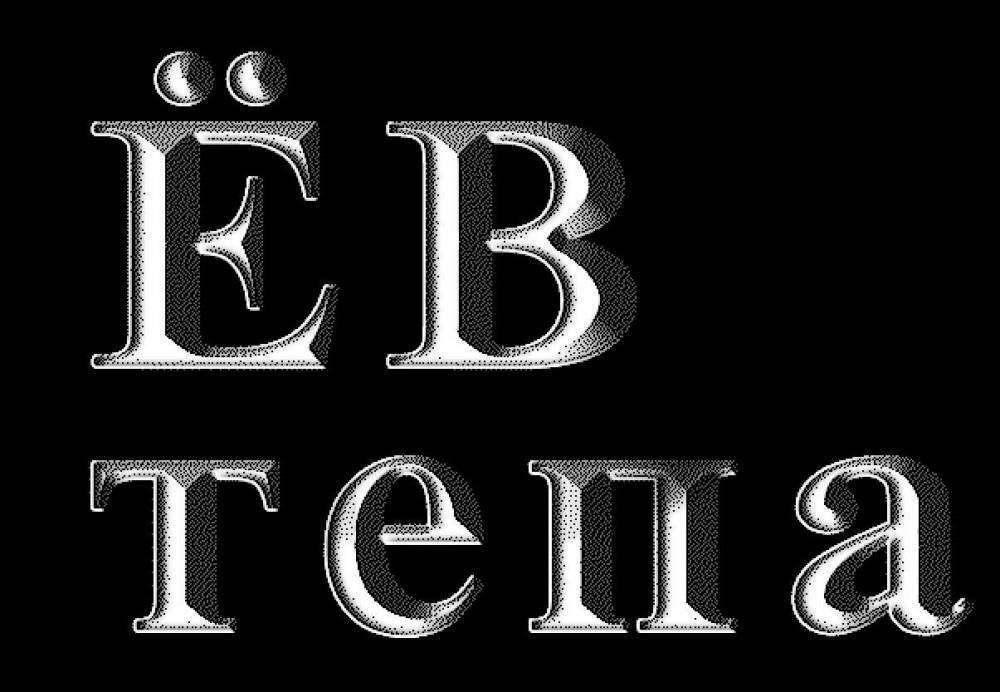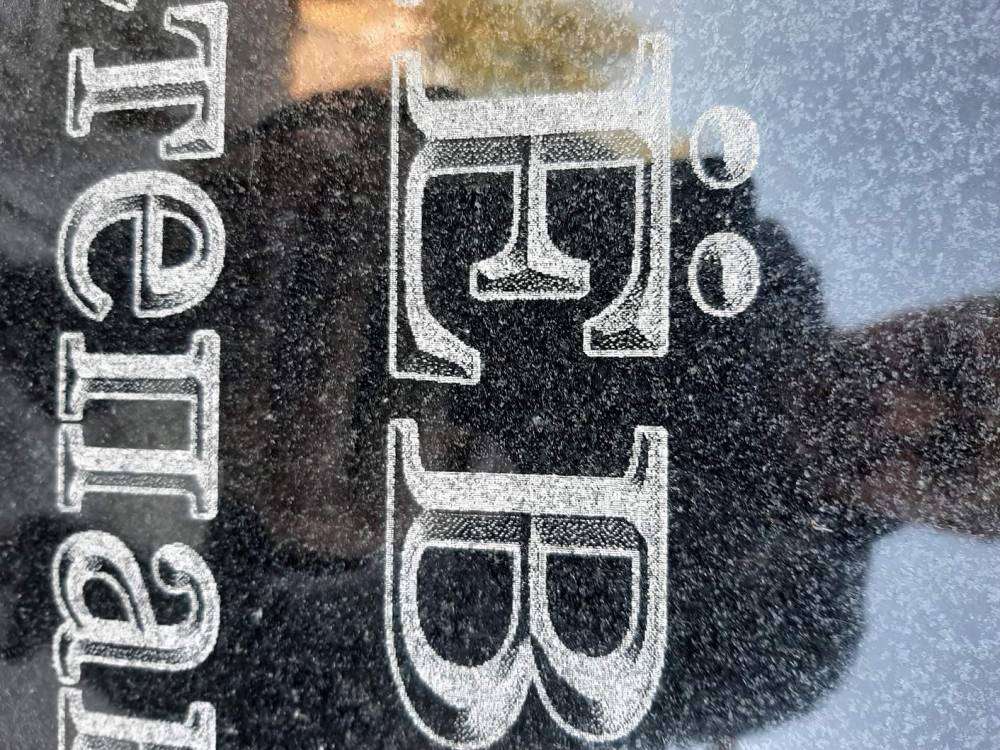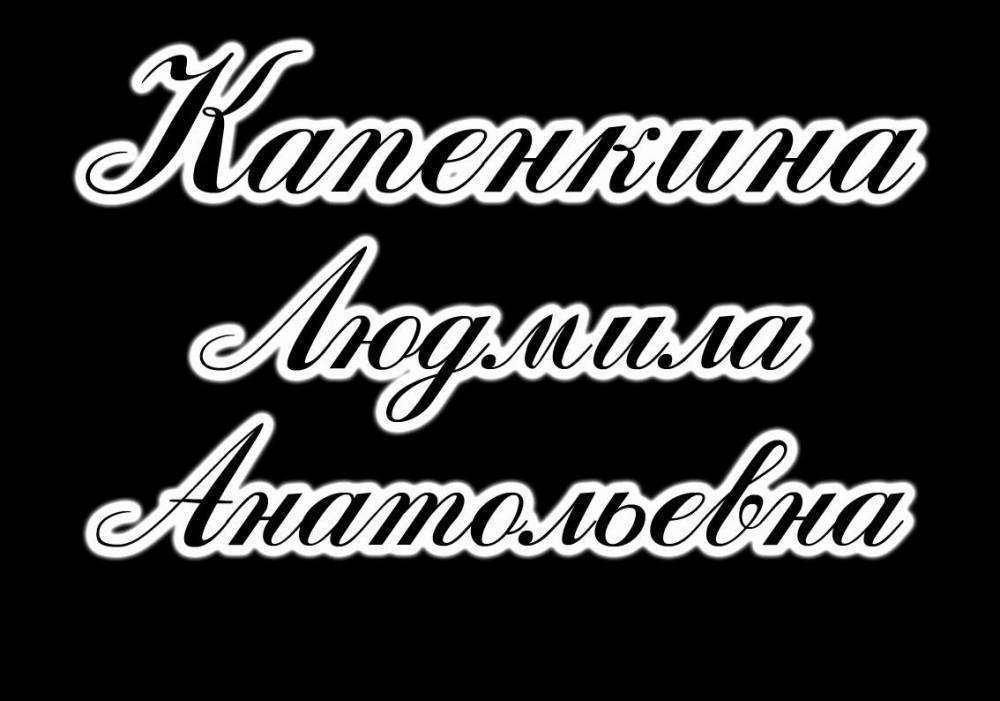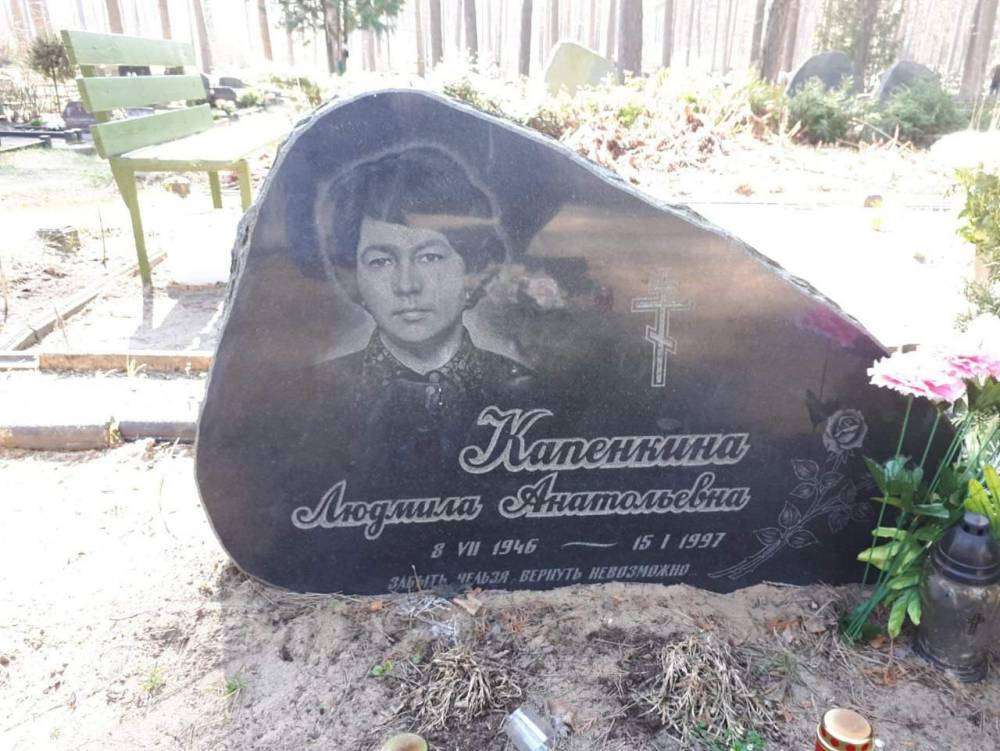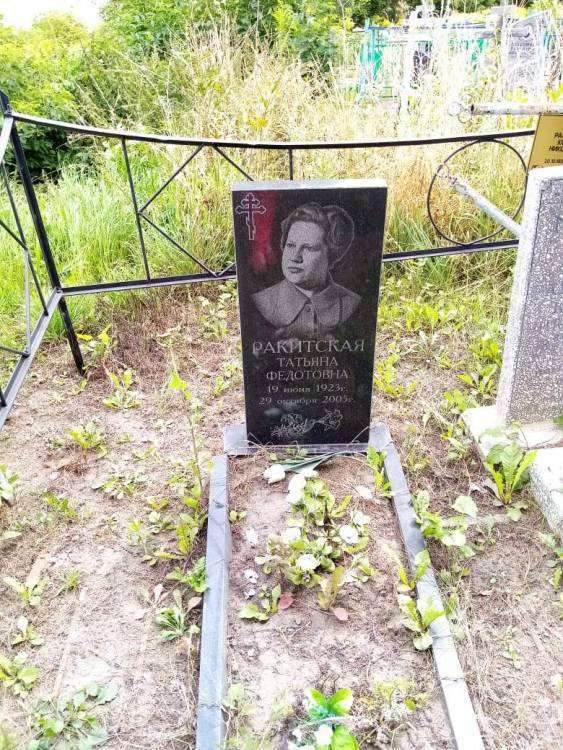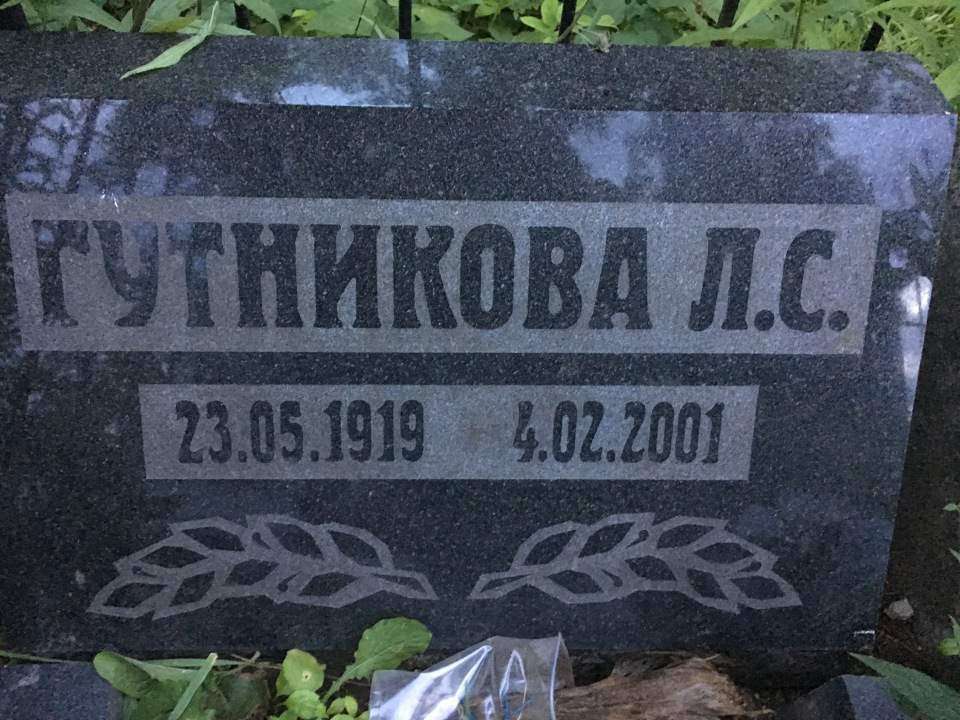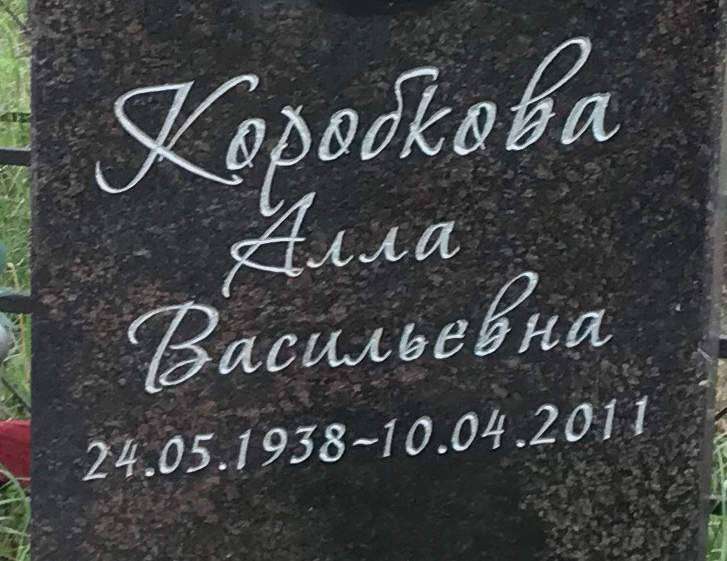
Помогите найти шрифт!
Подскажите, пожалуйста, шрифт похожий на этот
Подскажите шрифт, пожалуйста:
@Яшa a_MachinaOrto
В рекомендованном выше Л еще хуже.
Доброго. Подскажите что за шрифт.
@Михалыч73 , здесь дело не в шрифте, а в его стиле.
Шрифт, скорее всего, Times New Roman, к которому применены эффекты типа: тиснение, внутренняя тень, обводка и т.п.
Вот что у меня получилось с Times New Roman за пару минут:
Помогите! Как  называется шрифт?
Здравствуйте. Помогите найти шрифт
подскажите шрифты, пожалуйста.
оба - и фио, и эпитафию.
привет всем.помогите. ищу подобный шрифт
это ручной шрифт Calligraph и есть буковки из другого шрифта
Odessa Script
В общем...  помогите люди добрые.
с чем его едят ?
Vera Crouz
Здравствуйте, помогите пожалуйста найти такой шрифт